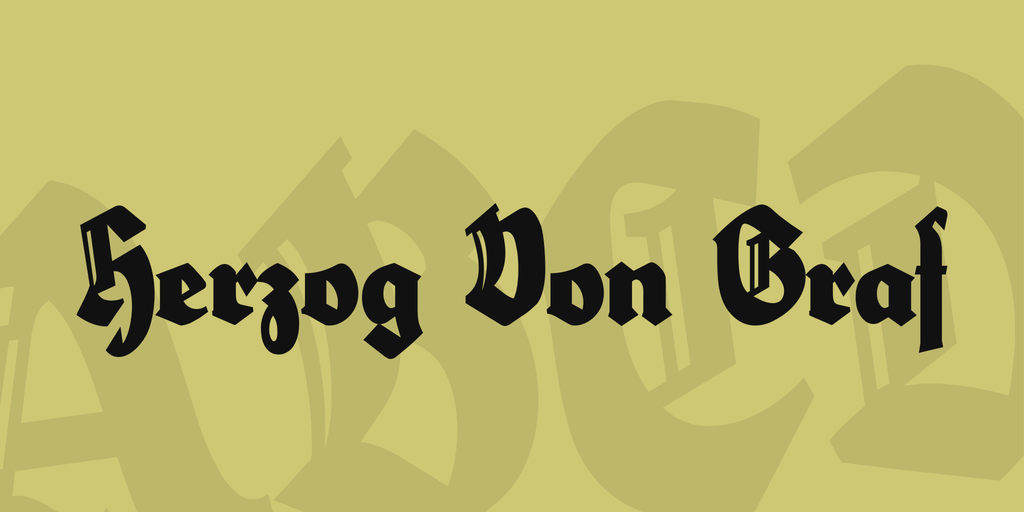
A fonte ‘Herzog Von Graf Font Family’, categorizada como Blackletter Fonts, foi criada por Hamilton e é uma evolução do famoso font Poseidon. Procurando por um bom font Deco Gótico para trabalhos mais formais ou artísticos, fomos capazes de encontrar exatamente o que buscávamos com esta criação. O designer original foi um mistério, mas Hamilton fez uma limpeza no design para tornar a fonte ainda mais robusta e séria. Ela tem uma sensação gótica sóbria, com um toque moderno de boldness. Além disso, como o nome traduz-se do alemão para “Duke of Earl”, podemos dizer que este é um texto forte, repleto de hierarquia. A fonte ‘Herzog Von Graf Font Family’ é perfeita para títulos e headlines, oferecendo uma aparição distinta sem ser demais. Seja você designer gráfico ou editor de textos, certamente encontrará um uso ótimo desta font poderosa.